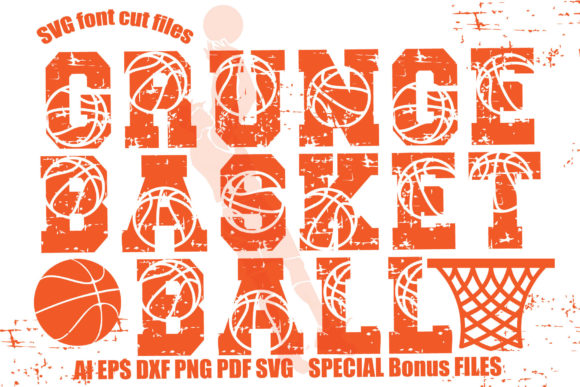
Grunge Basketball SVG Font Cut Files
หากคุณกำลังมองหาเนื้อหาคุณภาพสูงเช่น Grunge Basketball SVG Font Cut Files แพ็คเกจพรีเมียมนี้เป็นตัวเลือกที่ยอดเยี่ยมสำหรับโปรเจ็กต์สร้างสรรค์ของคุณ
สร้างขึ้นอย่างแม่นยำ Grunge Basketball SVG Font Cut Files ให้เวกเตอร์ที่สะอาด พิมพ์ตัวอักษรที่ราบรื่น และใบอนุญาตเชิงพาณิชย์เพื่อความสบายใจ